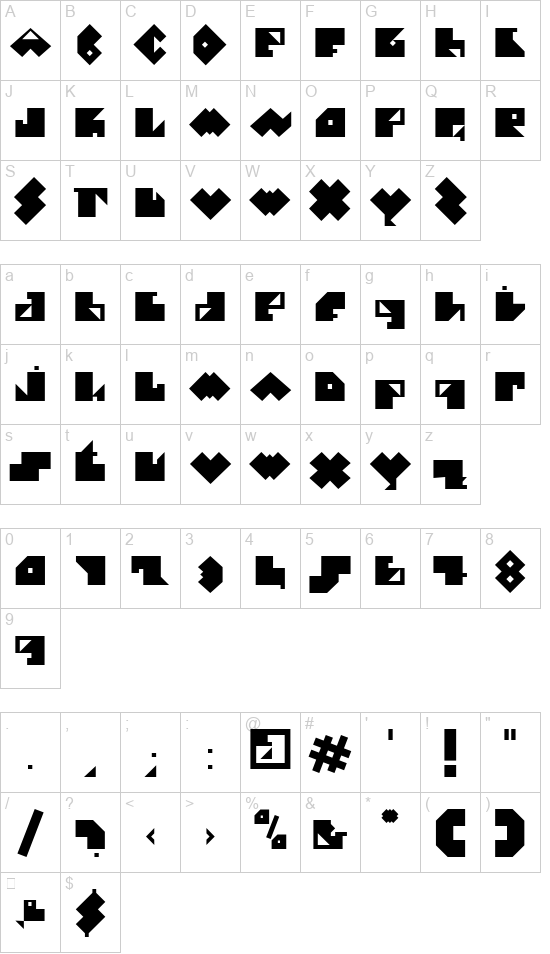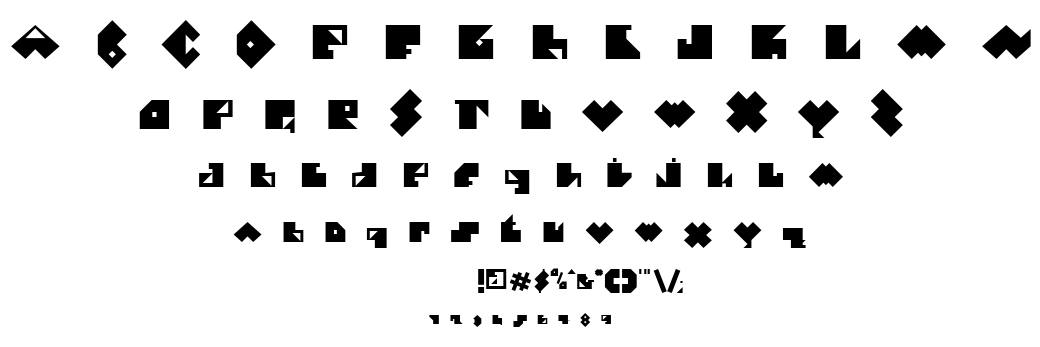
Esta tipografía experimental esta construida en su gran mayoría con las 3 piezas del imagotipo de mi logo: el pececito, un diseño geométrico y minimalista.